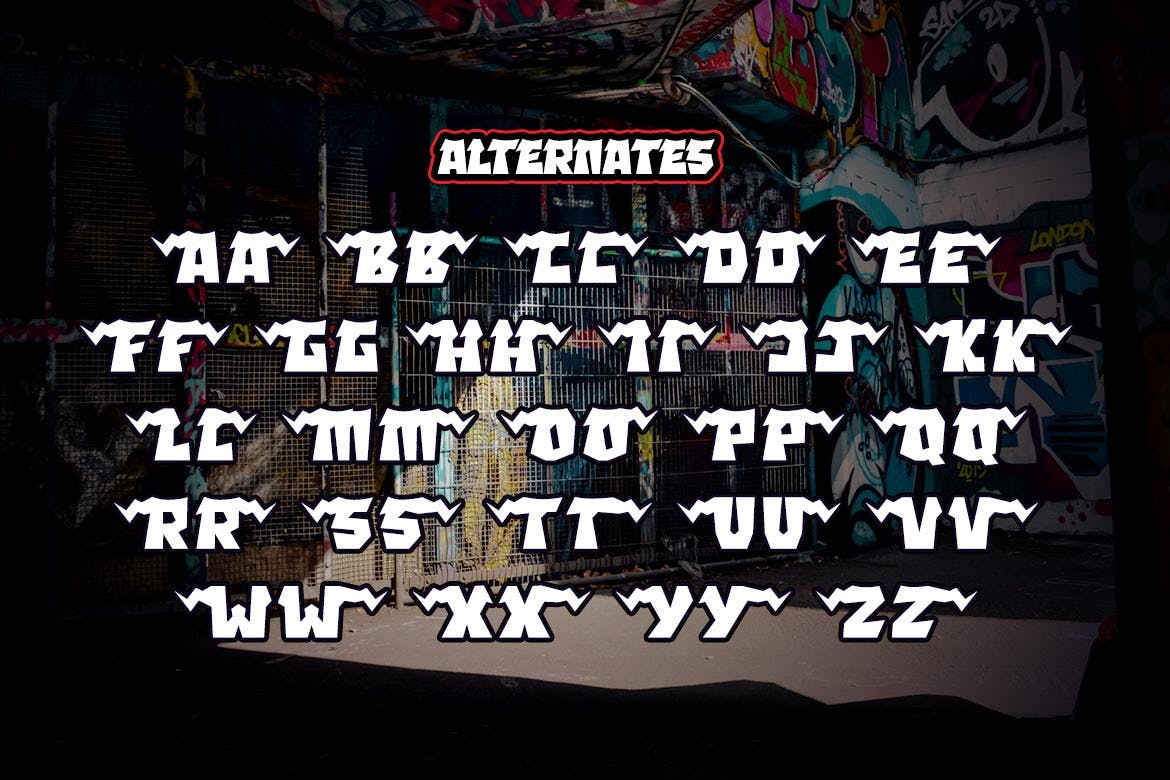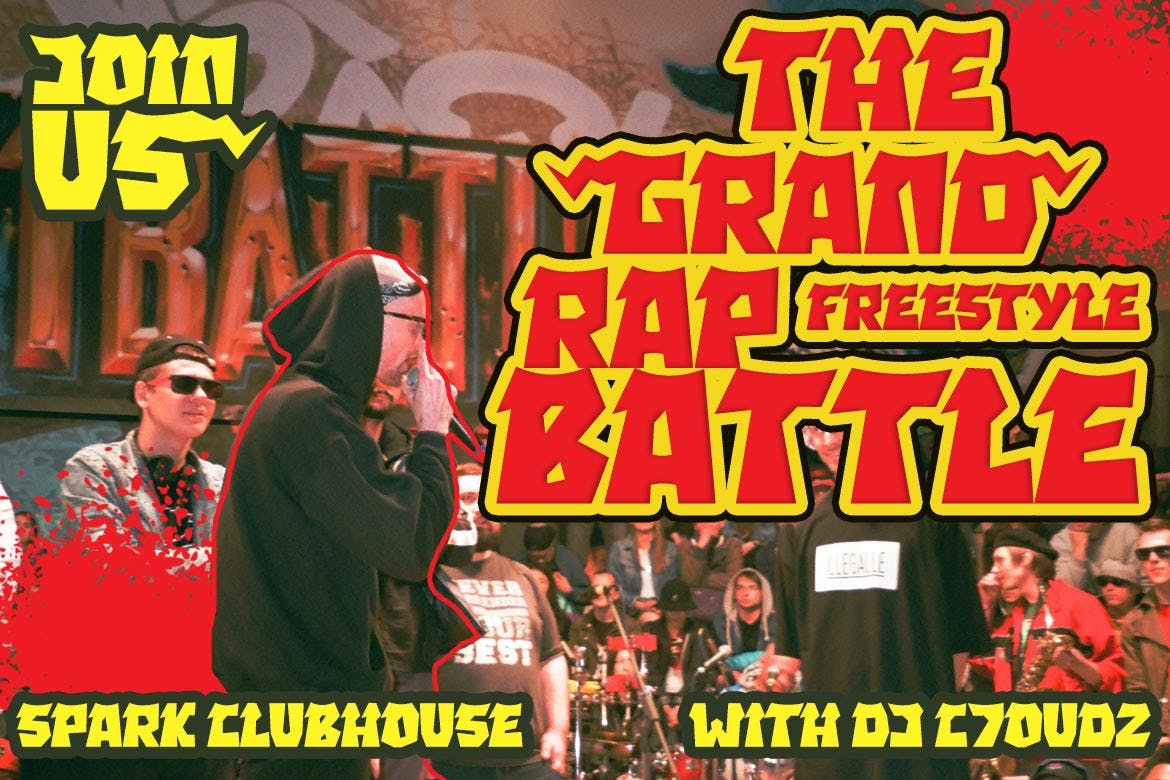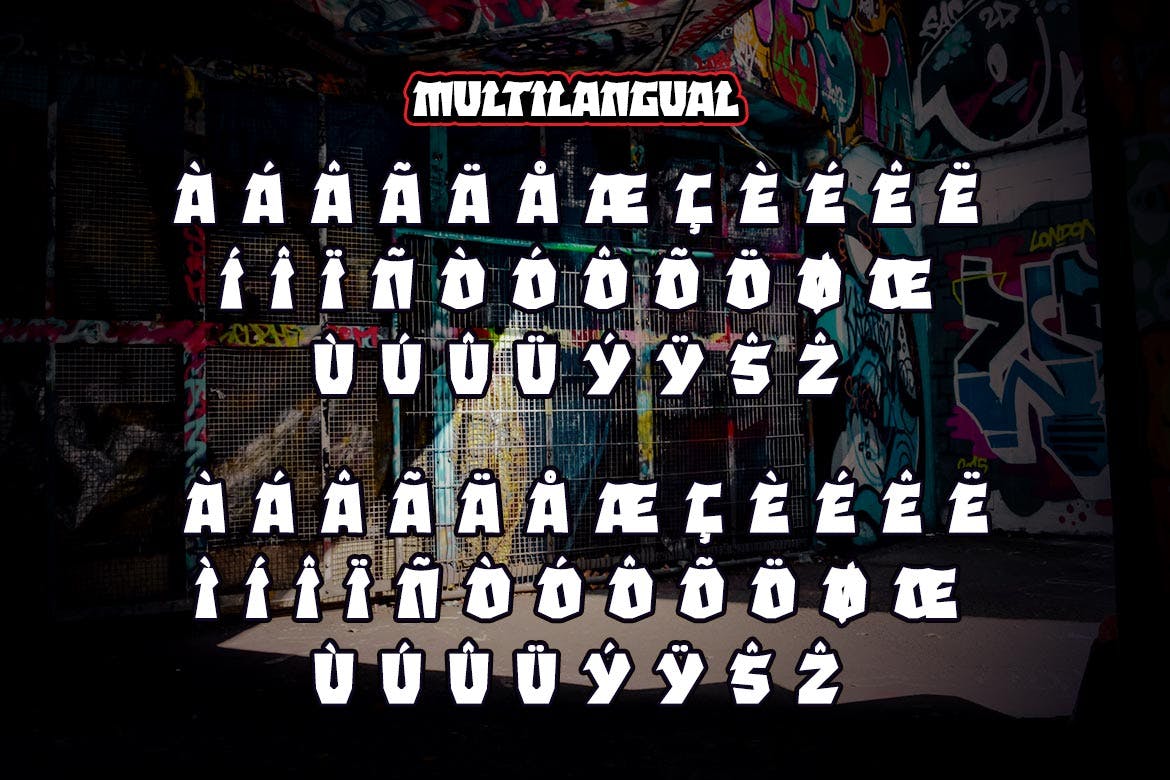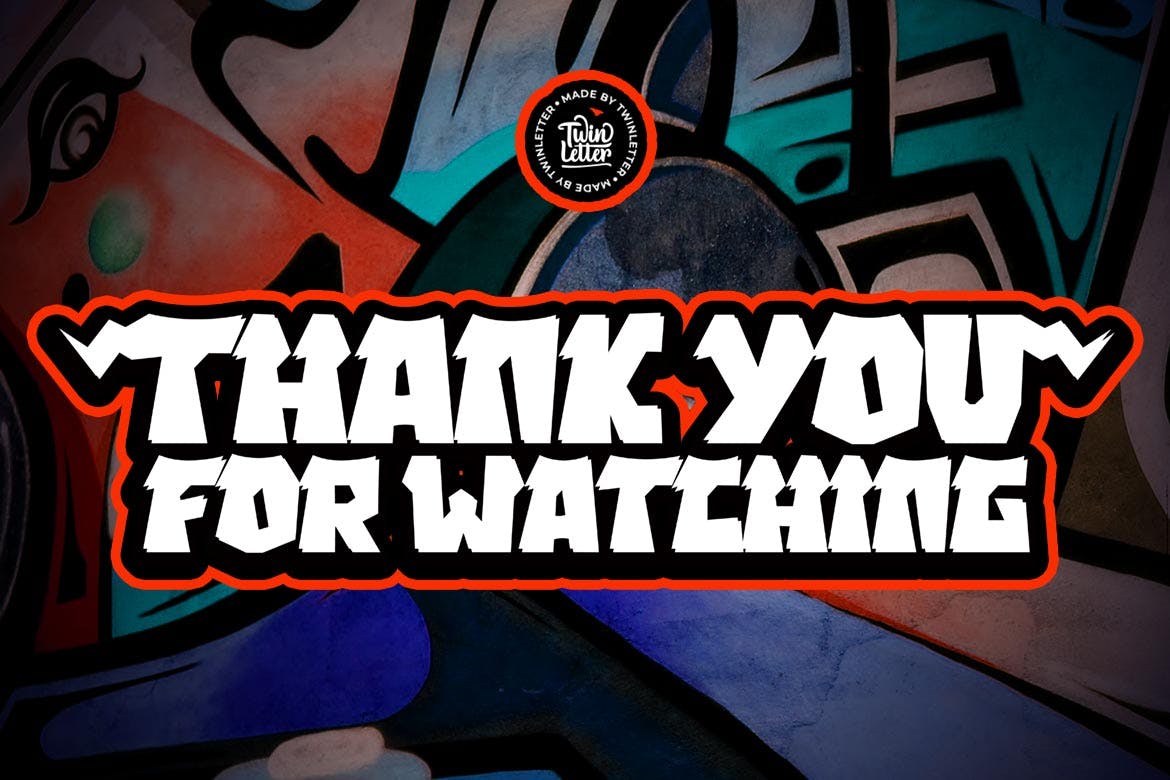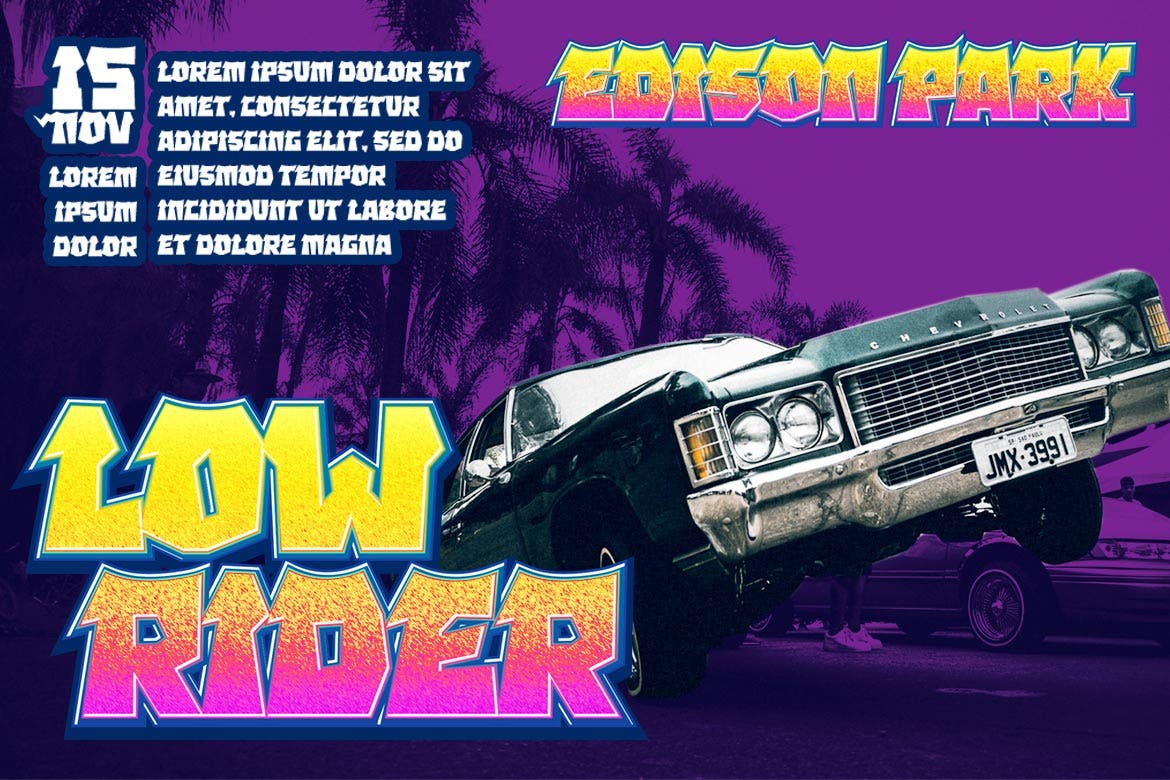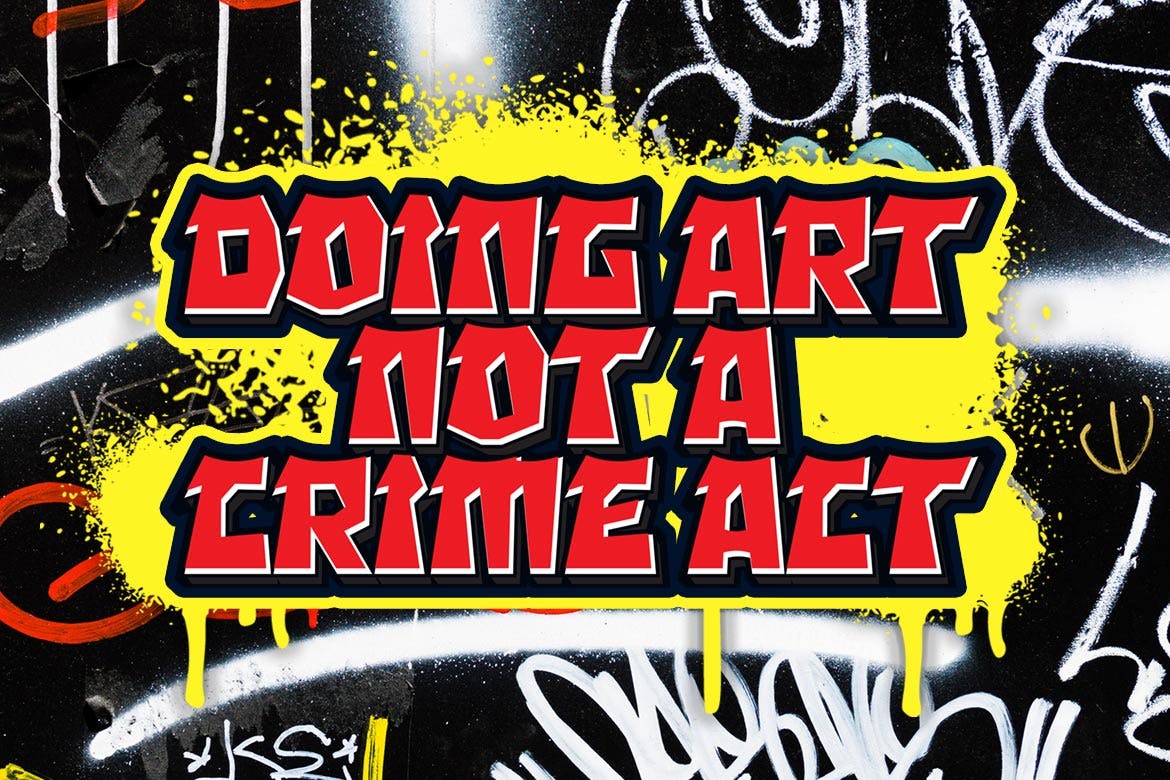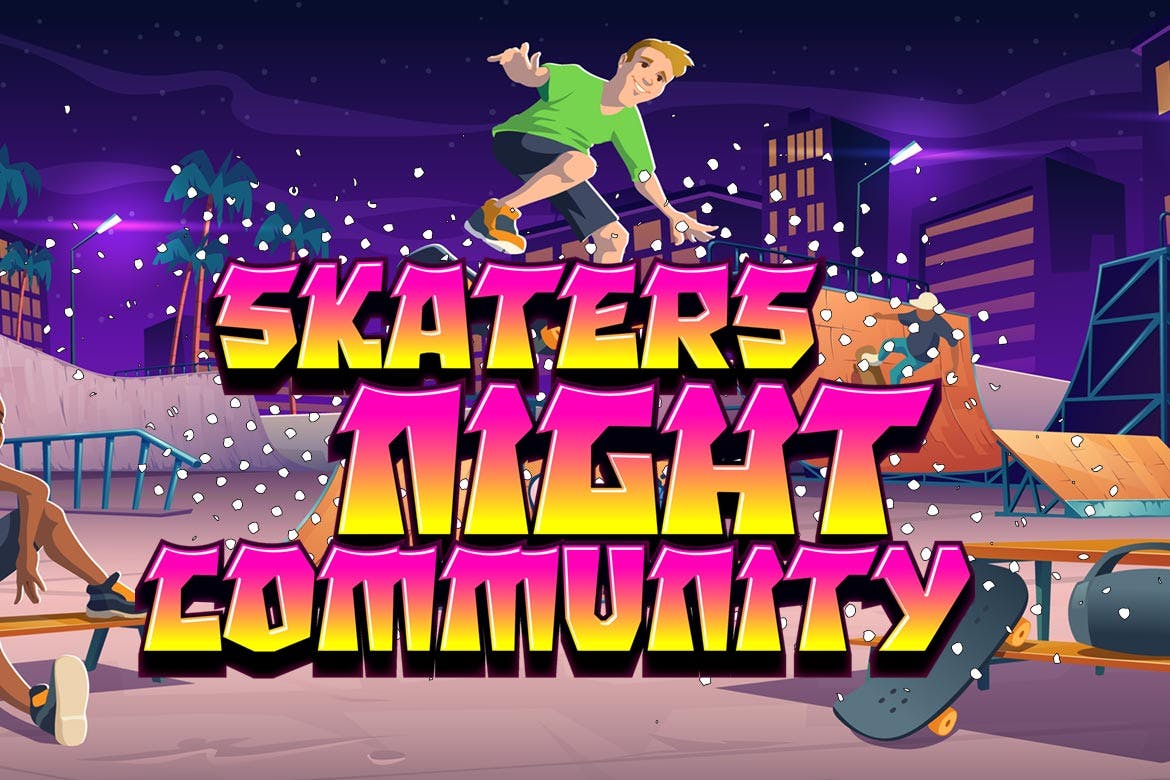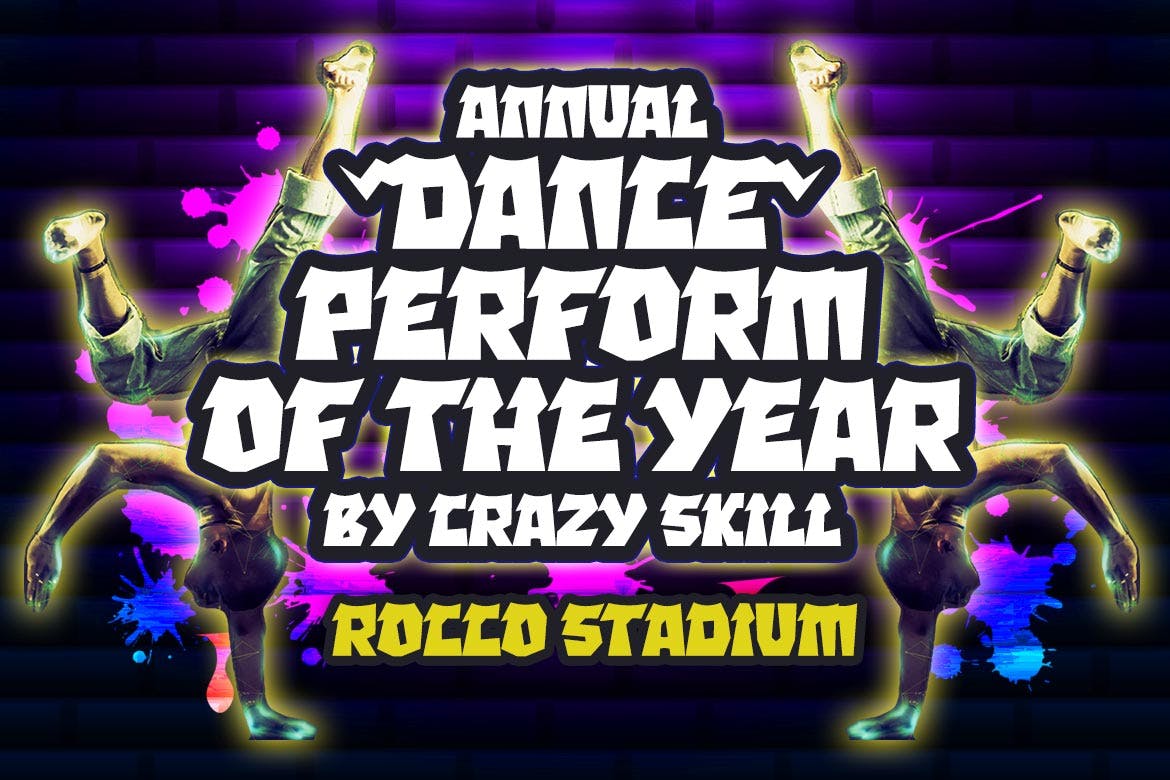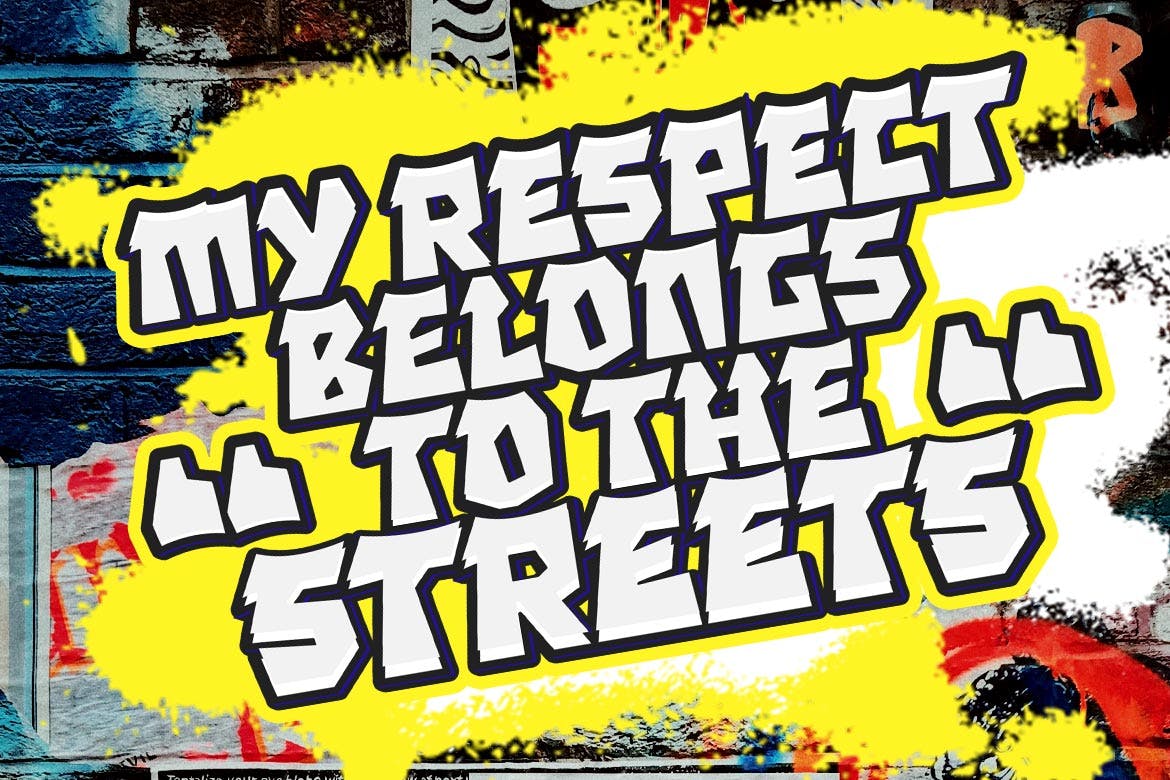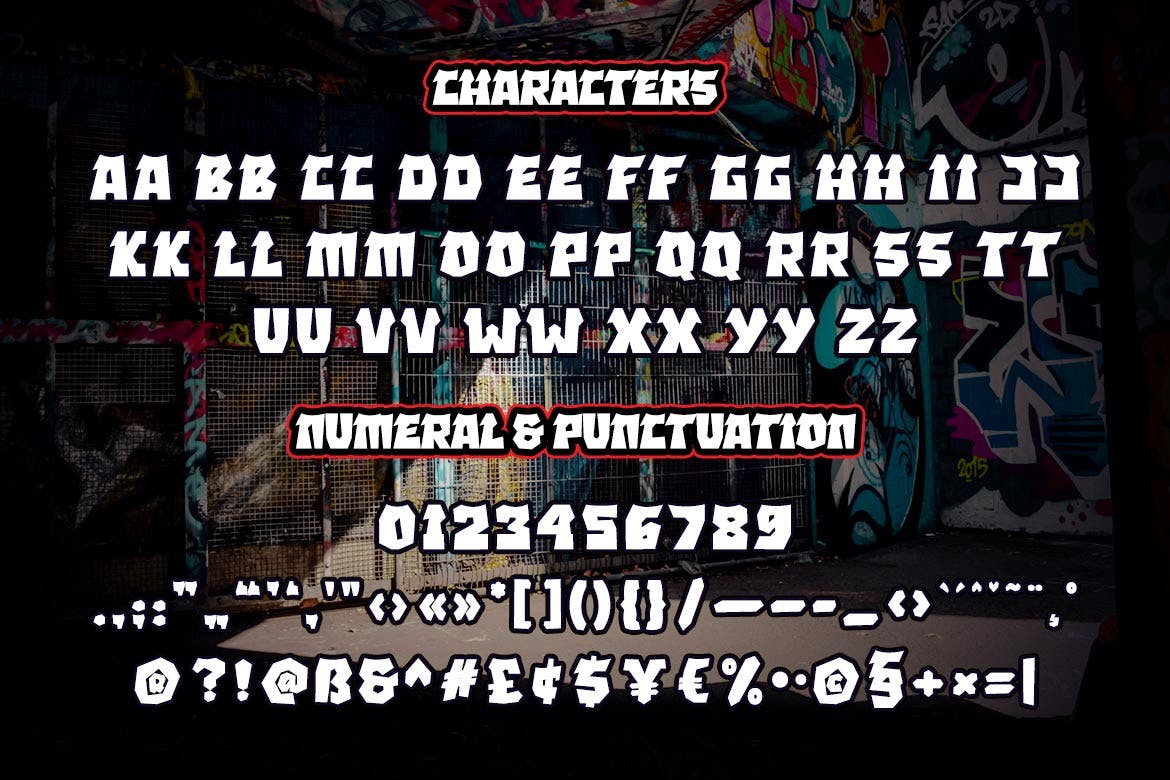
فونت MENOR یک فونت گرافیتی با شکلهای انتزاعی و جذاب است که هر کاراکتر آن ویژگیهای منحصر به فردی دارد و این فونت را برای پروژههای برجسته شما مناسب میسازد. این فونت همچنین شامل حروف بزرگ متنوعی است که به زیبایی پروژه شما کمک میکند، پس منتظر نمانید. با استفاده از این نوعخط، پروژهای زیبا و شیک خلق کنید.
این فونت گرافیتی برای طراحی لوگوهای محصولات، عناوین پوستر، تیترها، بستهبندی، عناوین فیلم، لوگوها، نوشتار زیبا و طراحیهای مدرن گرافیتی بسیار مناسب است.
بدون شک، اگر از این فونت در پروژههای خلاقانه خود استفاده کنید، نتایج آن فوقالعاده و بینظیر خواهد بود. همین حالا از این نوعخط برای پروژههای منحصر به فرد و شگفتانگیز خود استفاده کنید.